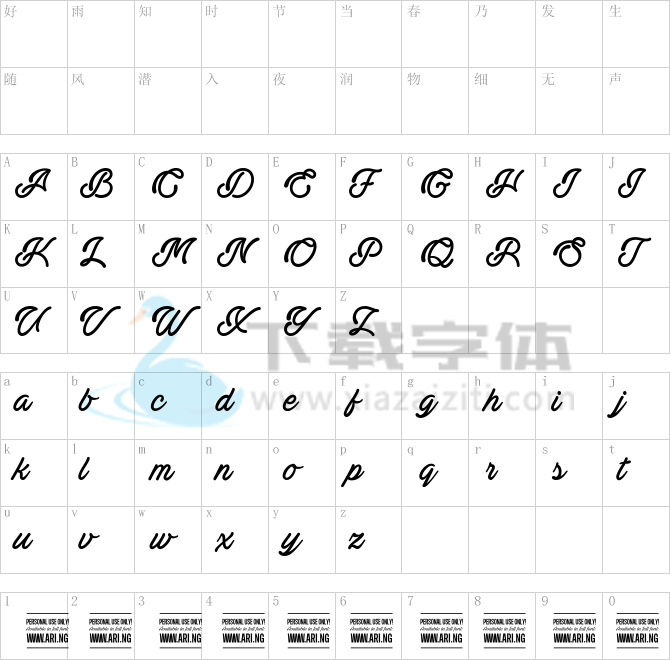
Actonia PERSONAL USE.ttf字体下载,这款字体结构工整、笔画清晰,兼顾美观与易读性,适用于标题、正文、海报、包装、LOGO 等多种场景。字形优雅稳定,风格百搭耐看,适配日常排版与创意设计,让文字呈现更舒适、更具质感。Actonia PERSONAL USE.ttf字体下载一笔一画,皆是细节,以均衡的比例、流畅的线条打造舒适视觉体验,字形端正大气,风格简约现代。无论是商业设计、品牌宣传还是日常排版,都能轻松驾驭,让文字更有格调与力量。Actonia PERSONAL USE.ttf字体下载字体下载。
• 字体名称:Actonia PERSONAL USE
• 字体全名:Actonia PERSONAL USE